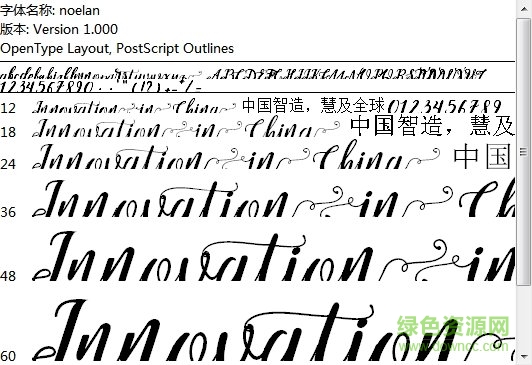
noelan字體,全稱noelan script,是一款有著花藤狀紋路的英文字體,連貫干凈,特別適合雜志封面、賀卡明星片、婚禮請柬的使用,綠色資源網(wǎng)獨家推薦!
Noelan Script是現(xiàn)代書法字體的不一樣的呈現(xiàn),它具有自動連接花飾以及交替給你的文字更多的人感受到很多,再加上國際字符。Noelan Script的花飾和交替讓文字看起來新鮮,免費(fèi)為個人和商業(yè)用途。
noelan字體有著非常干凈和現(xiàn)代的設(shè)計特色,包括大寫字母,小寫字母,數(shù)字或字符,讓文字變得更加鮮艷可口,使用性也很廣泛!